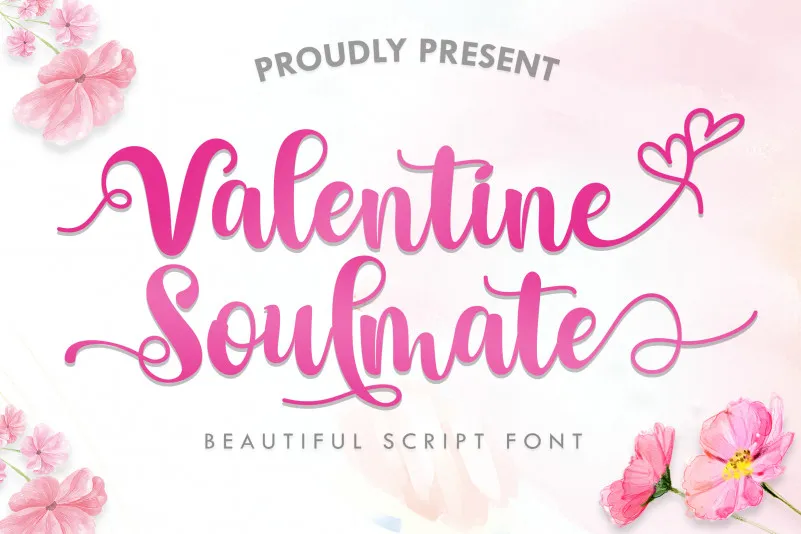
Valentine Soulmate Font – Download Grátis
A fonte Valentine Soulmate é perfeita para aqueles dias românticos do Dia dos Namorados, oferecendo linhas casualizadas com variedades de traços básicos, linhas finas e linhas clássicas e elegantes. Esse font script foi projetado especialmente para dar um toque delicado em qualquer projeto gráfico. Seja para uso em títulos, assinaturas, logotipos, convites de casamento, camisetas, assentos de carta, placas de nome, rótulos, notícias, panfletos ou selos, a font Valentine Soulmate é versátil e ideal para o seu próximo projeto. Com uma variedade de traços, esta fonte pode transformar qualquer projeto em algo único e autêntico. Não deixe de experimentar essa font perfeita para criar um visual elegante e romântico para seu trabalho gráfico.